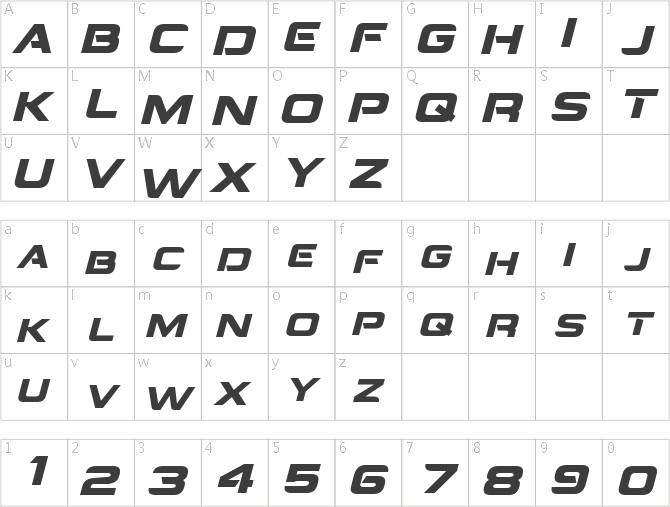
Montalban Italic 詳情頁
Montalban Italic
Montalban Italic介紹
Montalban Italic字體字庫是一款讓人賞心悅目、百看不厭的英文字體,適合各類廣告和產品包裝設計應用,字體大小0.02MB,格式為ttf字體,上傳用戶是隨緣゜,作者/版權方為未知
Montalban Italic效果圖